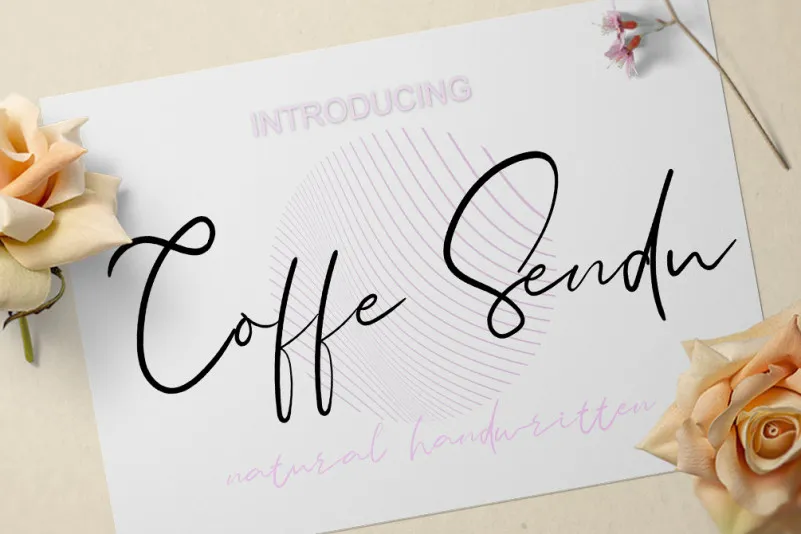
Coffe Sendu Font – Download Grátis
A fonte ‘Coffe Sendu Font’ é uma elegante escolha para aqueles que buscam personalidade e charme para seus projetos digitais. Seu design é inspirado na escrita a mão, mas com um toque de brilho e sofisticação, tornando-a uma opção incrivelmente valiosa para qualquer coleção de fontes. Este font será definitivamente sua próxima escolha quando está procurando por algo diferente que possa destacar seus designs em cada projeto. ‘Coffe Sendu Font’ é perfeita tanto para aplicações digitais quanto impressões, oferecendo uma textura agradável que vai da elegância de letras cursivas até a descontração de um estilo casual. Essencialmente, esta font transmite a calma e o conforto que uma boa chávena de café consegue proporcionar – só que em sua forma mais digital. Com ‘Coffe Sendu Font’, você encontra um verdadeiro tesouro para qualquer projeto de design.
Designer: Genarastudio